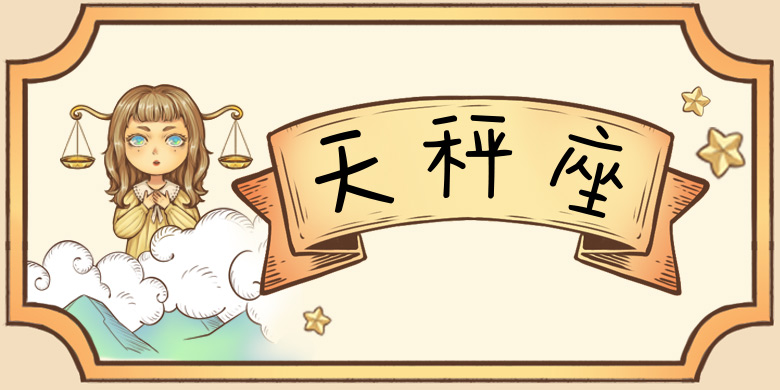
品牌:方正手迹设计师:俞亦婷发行时间:2019字库编码:简繁扩展(GBK)分类:创意书写字体属性:精品字
结构错置有序,书风活泼有趣,拙中有巧,活泼耐看。字体大小变化有序,阅读中能感受到字体的愉悦。字里行间,都透露着可爱的感觉。适用于少年儿童类的书刊、品牌广告和产品包装设计,以及社交网络的个性化用字。